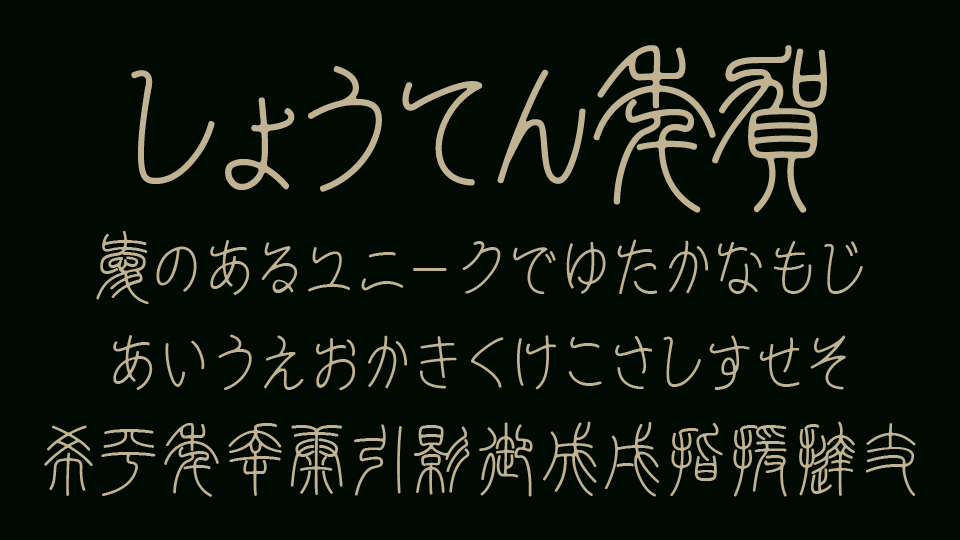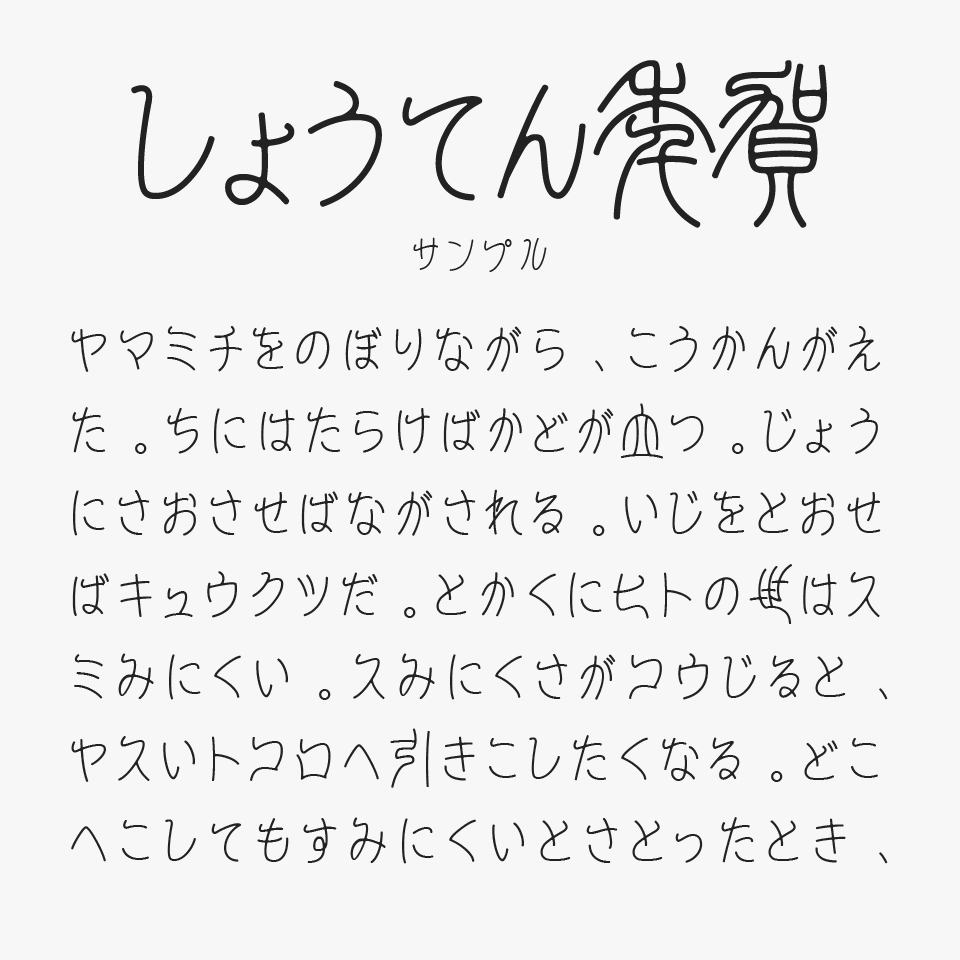
白舟小篆年賀
白舟小篆年賀フォントは、小篆をベースにしながら、細く流れるような筆の線でやわらかく仕上げられたフォントです。
筆でさらりと書き上げたような軽やかさがあり、漢字には小篆らしい独特の字形や装飾的な表情が残されているため、素朴な手書き文字とはひと味違った、古風で華やかな雰囲気があります。
年賀状での使用を目的に制作されており、新年のあいさつに使いやすい漢字が収録されています。小篆をベースとしながらも堅苦しさはなく、やさしい筆文字と手書きならではの温もりを感じられるところも魅力です。
小篆書体をベースとしたフリーフォントは珍しく、和風のデザインで少し変わった筆文字を使いたいときのために、持っておきたいフォントです。
収録文字は、漢字・ひらがな・カタカナ・数字・記号が収録されています。